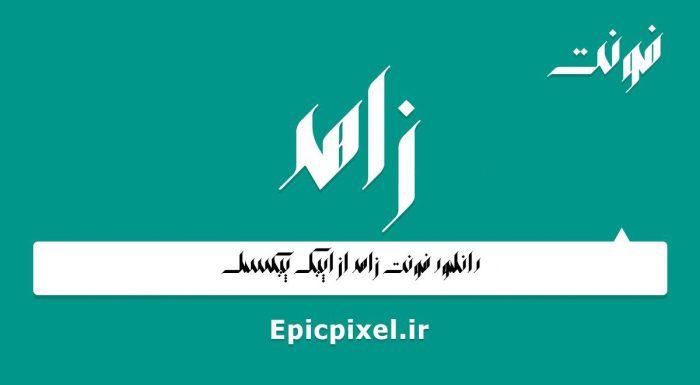
فونت زاهد فارسی
برای بهره مندی از زیبایی خط نستعلیق و ایجاد طرح های گرافیکی و متون فارسی با ظاهری دلنشین و اصیل، بسیاری از طراحان و کاربران علاقه مند به دانلود فونت زاهد فارسی هستند؛ چرا که این فونت رایگان، با الهام از خط زیبای نستعلیق، حروف و کلمات را به شکلی روان و خوانا نمایش می دهد و به دلیل تطبیق با استانداردهای تایپوگرافی، در نرم افزارهای مختلف طراحی به راحتی قابل استفاده است.
یک فونت خاص و جذاب برای عاشقای تایپوگرافی